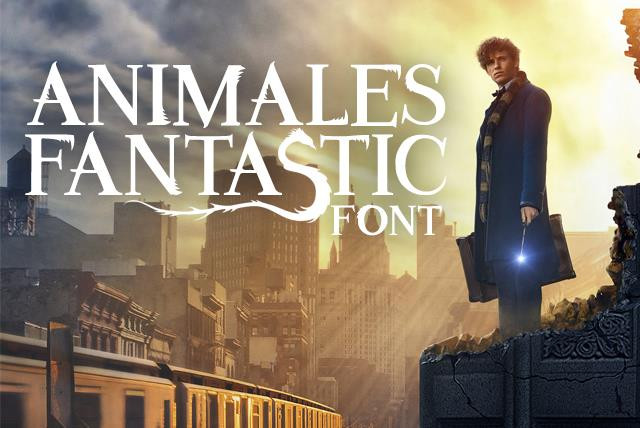
Animales Fantastic Font
Animales Fantastic Font — By FZ
Tipografia de ANIMALES FANTÁSTICOS Y DONDE ENCONTRARLOS
Font of FANTASTIC BEASTS AND WHERE THEN FIND THEM